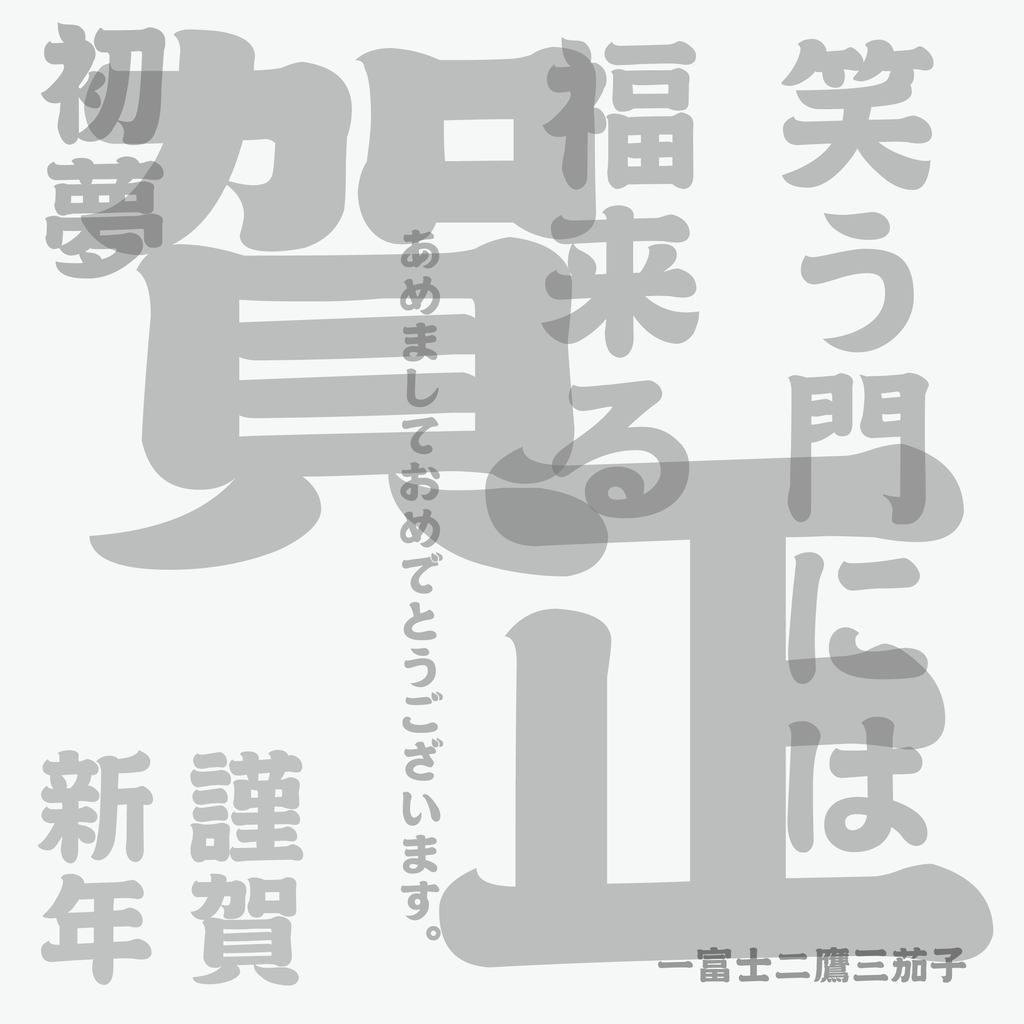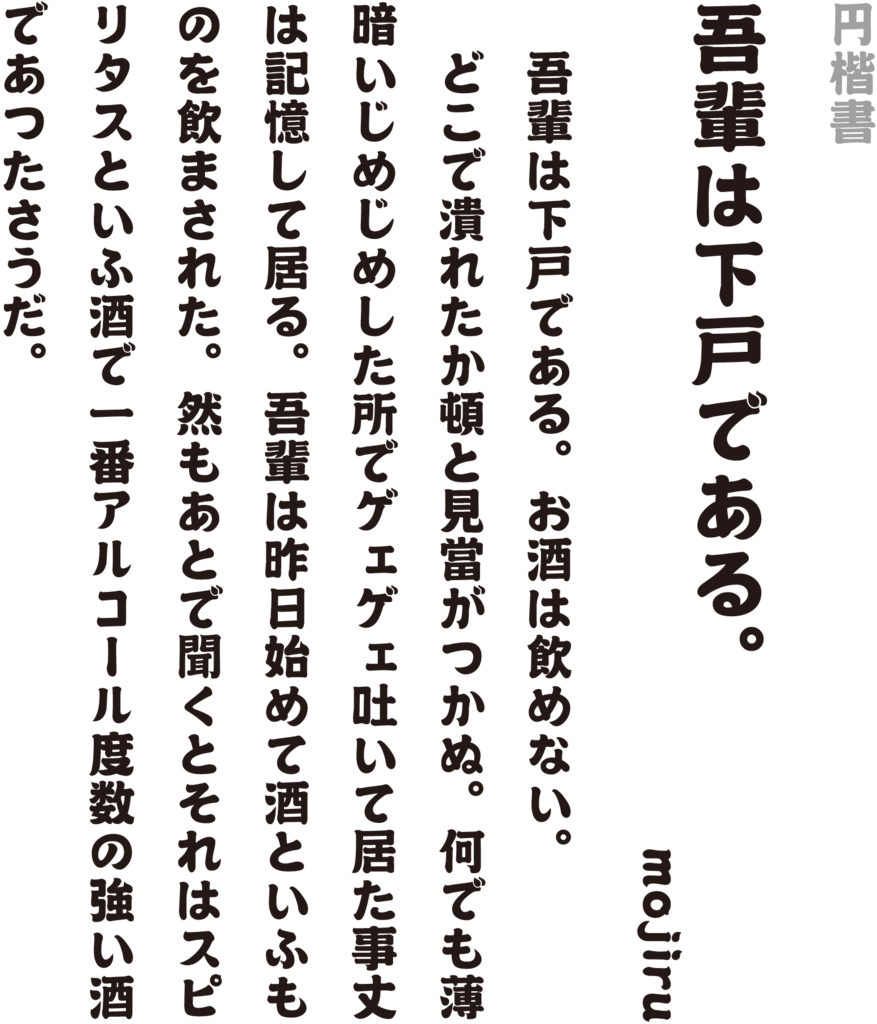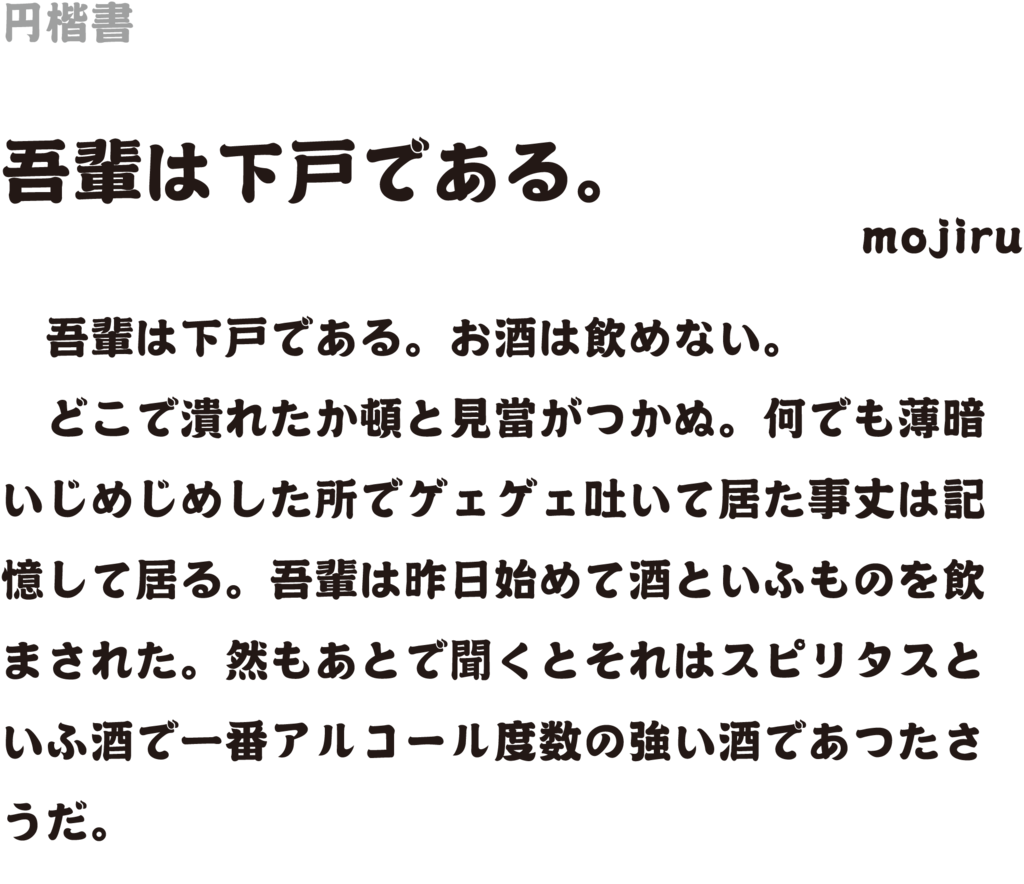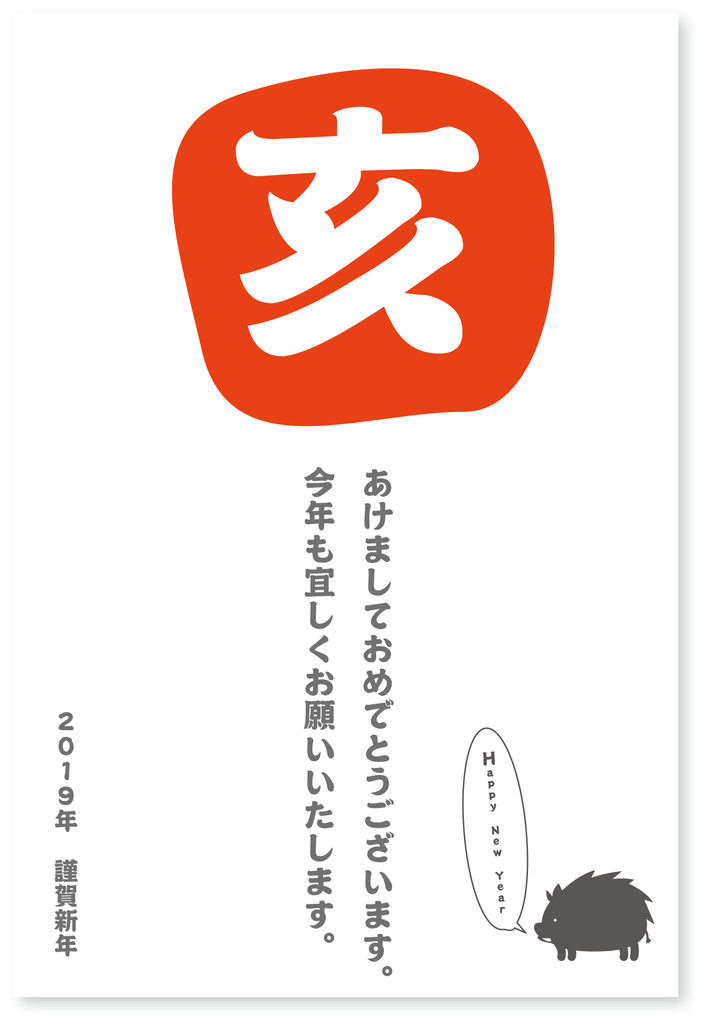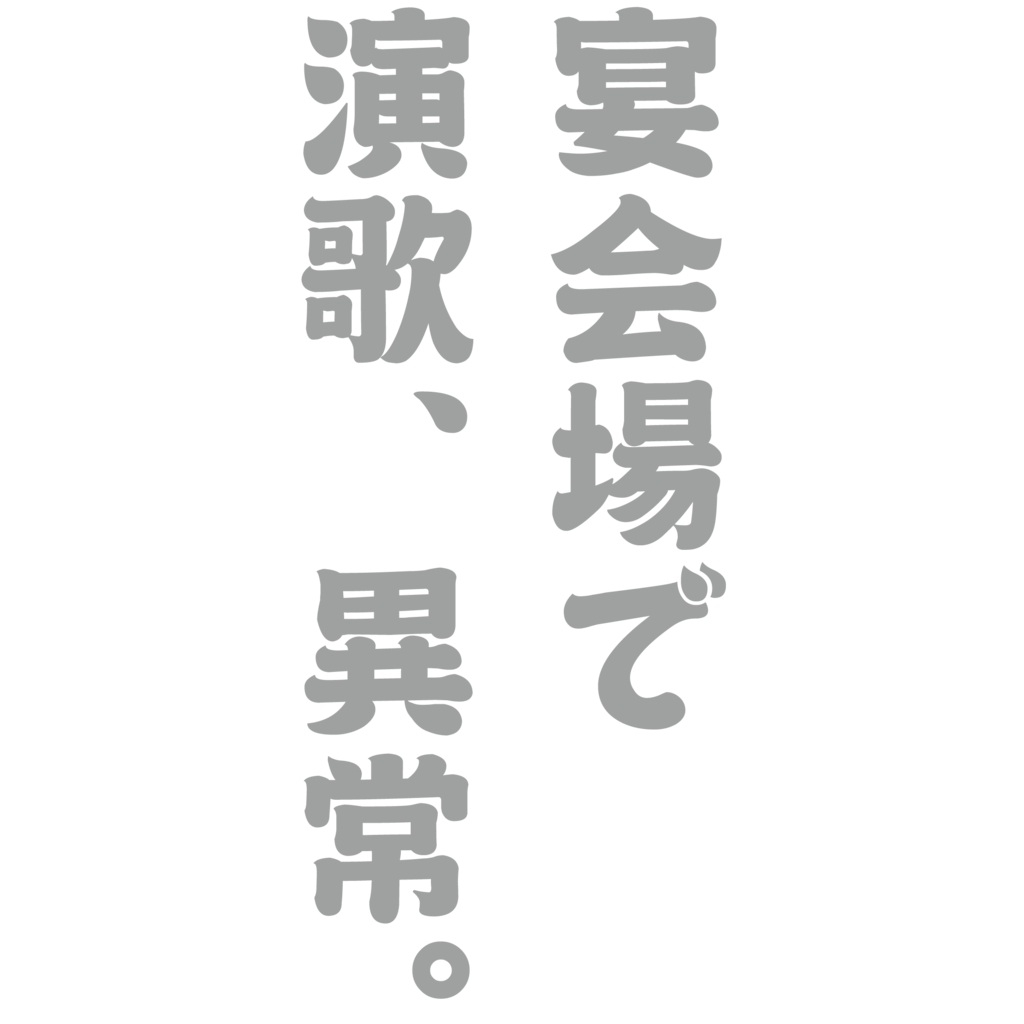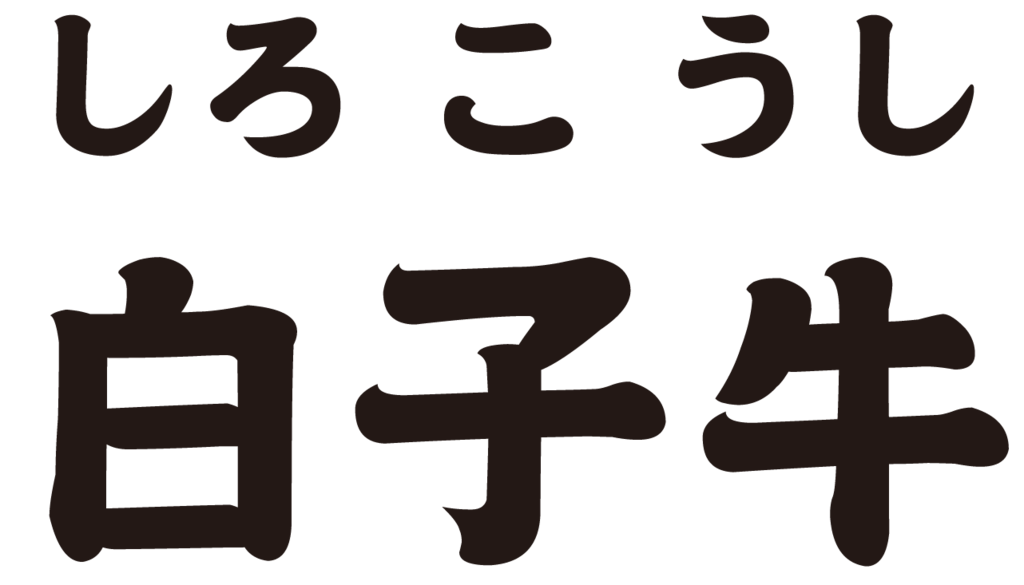
円楷書
太く丸みのある筆勢により穏やかな一面と力強さを兼ね備えた楷書体。
円楷書の書体見本
「ハナマルキ 液体塩こうじ」のパッケージタイトルに「円楷書」が採用
「ハナマルキ 液体塩こうじ」のパッケージタイトルのフォントに円楷書が使用されている。
NHKの「連続テレビ小説 エール」のオープニングに「円楷書」が採用
NHKの「連続テレビ小説 エール」のオープニングの文字に「円楷書」が採用されている。